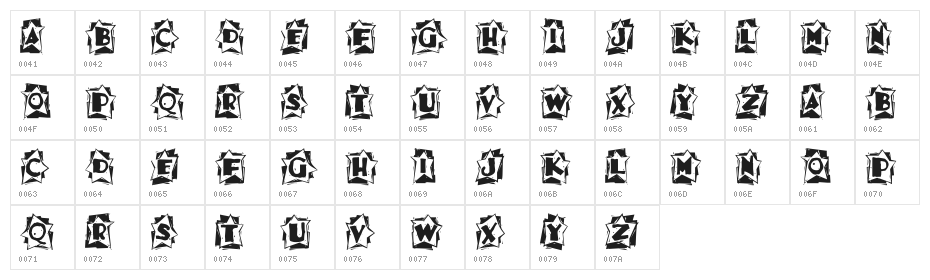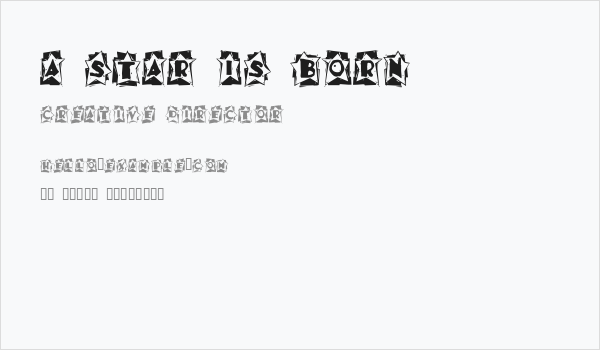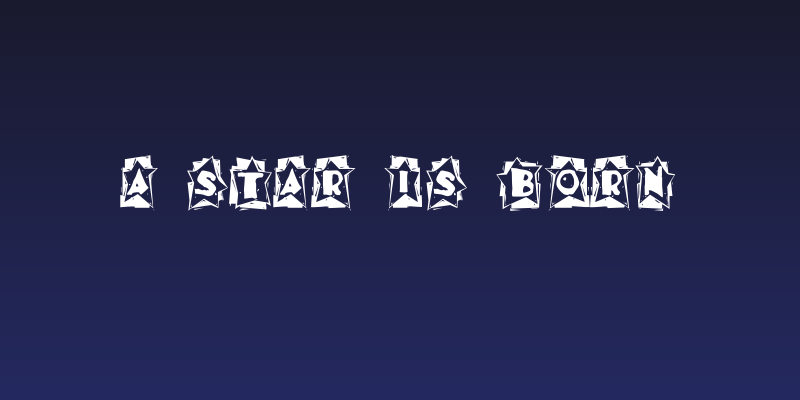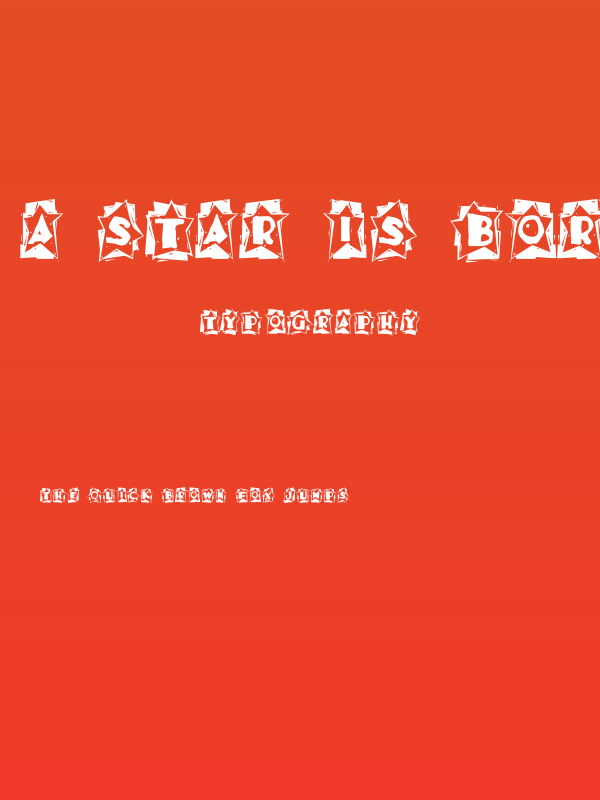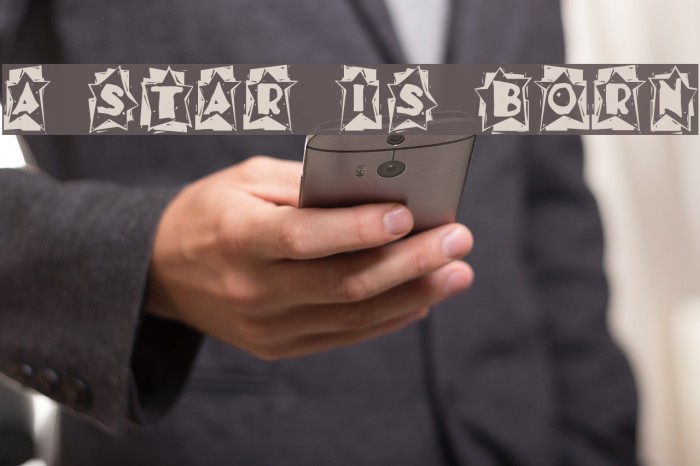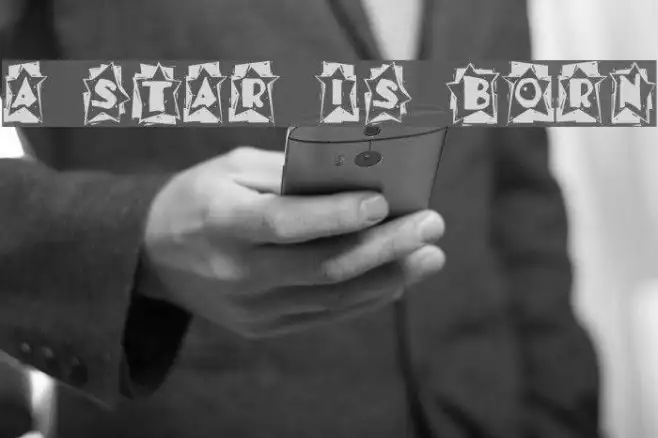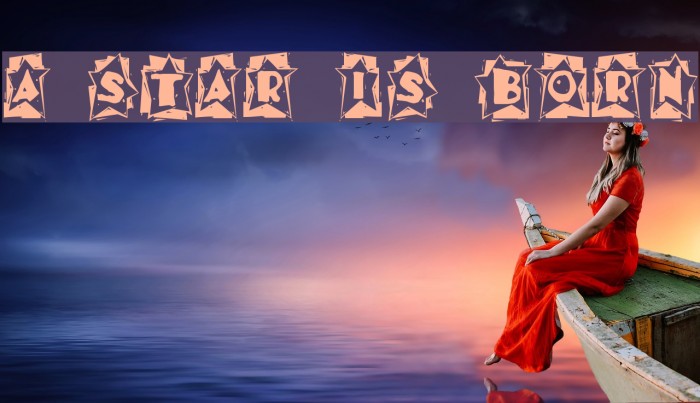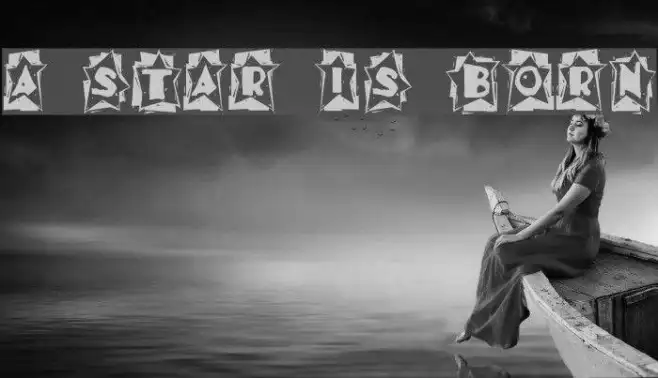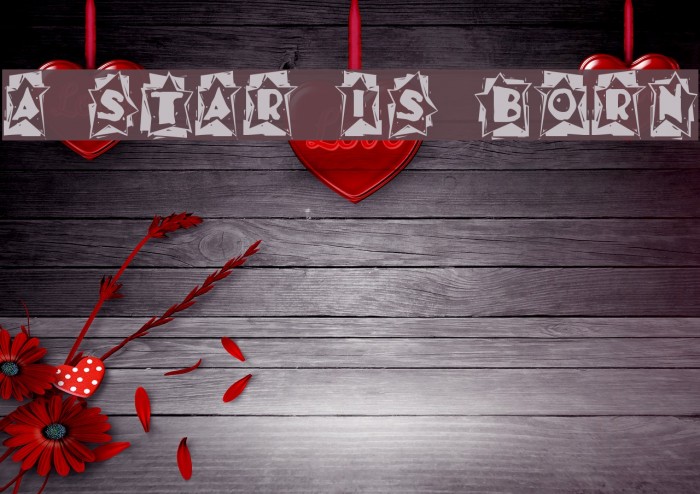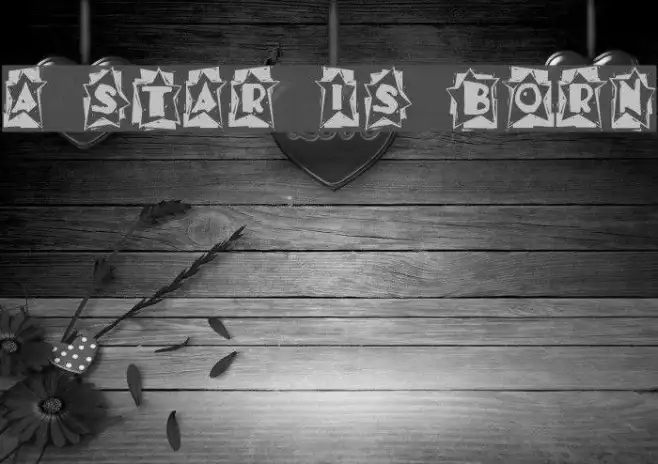
A Star is Born Font
✎ Decorative
| Vorgeschlagene Projekte | Ideal for posters, album covers, event flyers, and any project requiring a bold, artistic touch. |